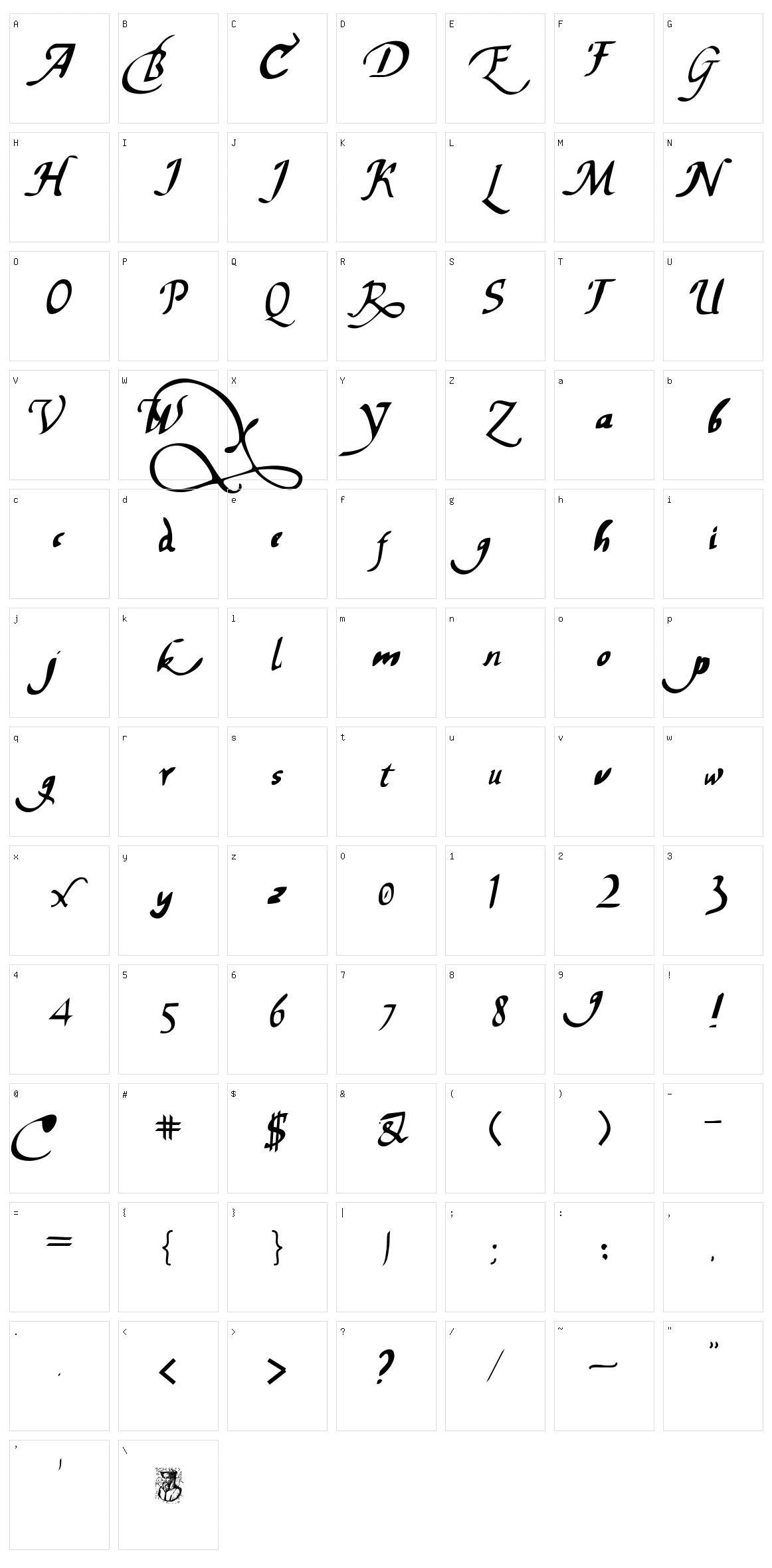
CHANCELARESCA PW
baseada na escrita de estilo caligrafico medieval chancelaresca
CHANCELARESCA PW TRUE TYPE FONT
based in the Middle Ages writing style named "chancelaresca"